Jak zmienić czcionki na Instagramie w swoim profilu i podpisach
Chociaż Instagram oferuje dziewięć różnych czcionek do wykorzystania w swoich relacjach, twój profil oraz standardowe podpisy i komentarze pozostają z jednym, dość monotonnym krojem bezszeryfowym. Poniżej przedstawiamy sposoby na urozmaicenie tej sytuacji.
Zasady działania niestandardowych czcionek na Instagramie
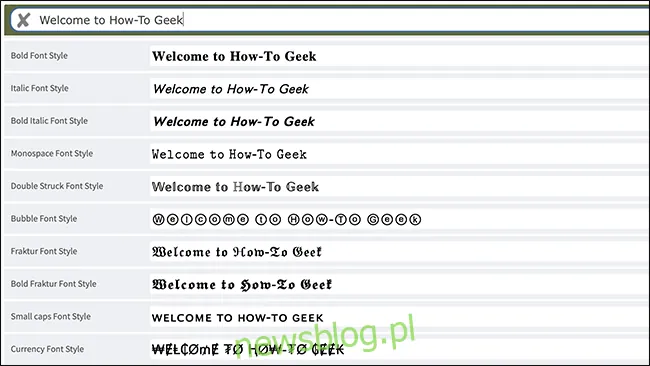
W przypadku małych tekstów, takich jak komentarze i podpisy, Instagram korzysta z czcionki Proxima Nova. Niestety, nie ma możliwości jej zmiany, ale istnieją sposoby, aby to obejść.
Instagram obsługuje również wiele skryptów Unicode, co pozwala na wykorzystanie różnych alfabetów, znaków interpunkcyjnych oraz emoji. Wśród obsługiwanych znaków znajdują się m.in. symbole matematyczne (÷), greckie litery (Ω) i hebrajskie znaki (א), a także różne style liter, takie jak: 𝓬𝓱𝓪𝓻𝓪𝓬𝓽𝓮𝓻𝓼, 𝒻𝑜𝓃𝓉𝓈 𝒶𝓃𝒹 𝒷𝓊𝓈𝓎 𝓈𝓎𝓶𝓫𝑜𝓁𝓈. Można także łączyć różne glify, co umożliwia tworzenie nietypowych efektów, jak odwrócone litery (ʇuoɟ uʍop ǝpısdn uɐ) oraz inne kreatywne znaki.
Teraz, gdy rozumiesz zasady, przyjrzyjmy się, jak łatwo można korzystać z tych niestandardowych czcionek na Instagramie.
Jak dodać niestandardowe czcionki do opisów i biografii
Choć niektóre znaki Unicode można wprowadzić za pomocą standardowej klawiatury, dla bardziej skomplikowanych efektów lepiej jest skorzystać z odpowiednich aplikacji do kopiowania i wklejania tekstu.
Na swoim smartfonie wejdź na stronę CoolFont.org i wpisz swój podpis lub komentarz. Otrzymasz około 100 różnych stylów tekstu, od atrakcyjnych po ledwo czytelne. Jeśli chcesz dodać dekoracje, takie jak serca czy gwiazdki, dotknij przycisku „Udekoruj”.
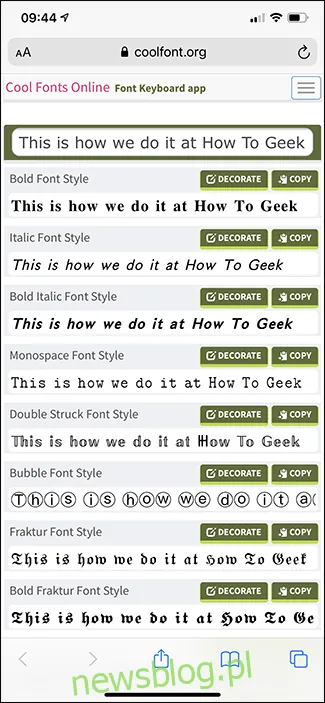
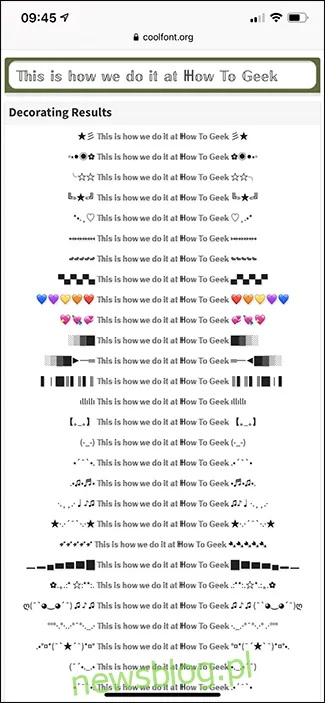
Kiedy uzyskasz satysfakcjonujący efekt, zaznacz tekst i skopiuj go. Następnie możesz wkleić go w dowolnym miejscu na Instagramie.
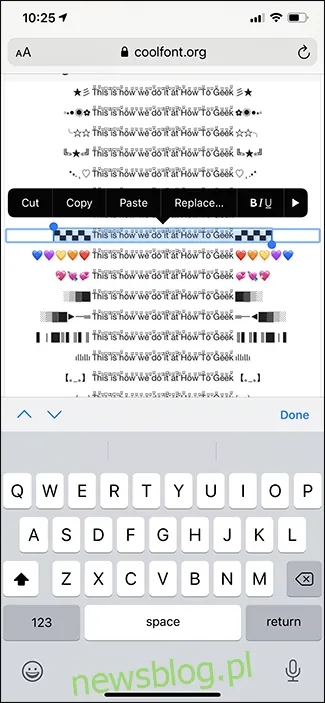
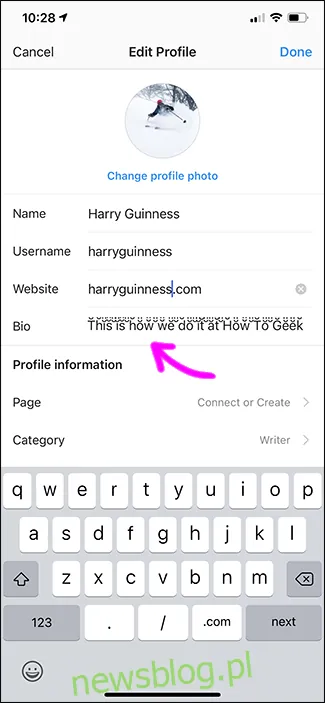
Ta metoda działa również w przypadku relacji na Instagramie, chociaż efekt może nie być tak atrakcyjny jak przy użyciu domyślnych czcionek.
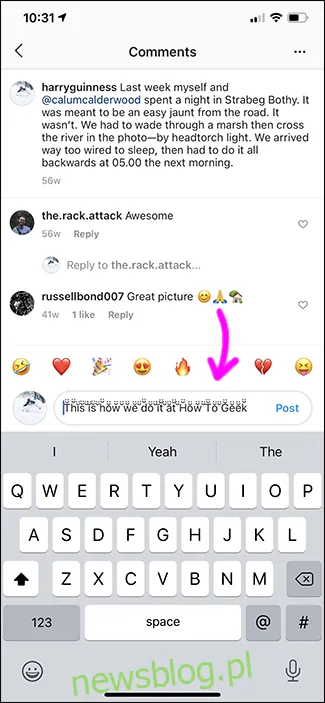
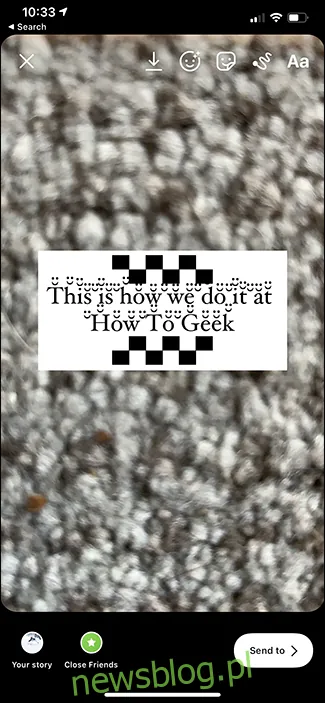
Możesz zastosować tę samą technikę, aby dodać zabawne czcionki także w innych serwisach społecznościowych wspierających Unicode, jak Twitter czy Facebook. Pamiętaj jednak, aby tekst był dalej czytelny dla odbiorców.